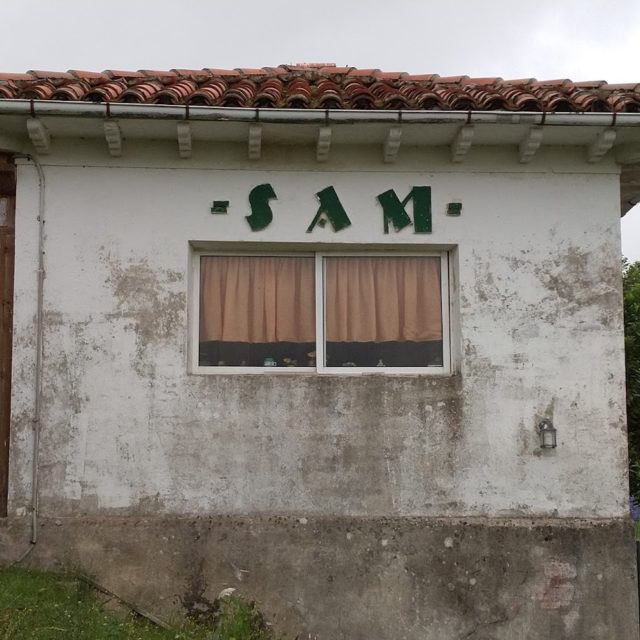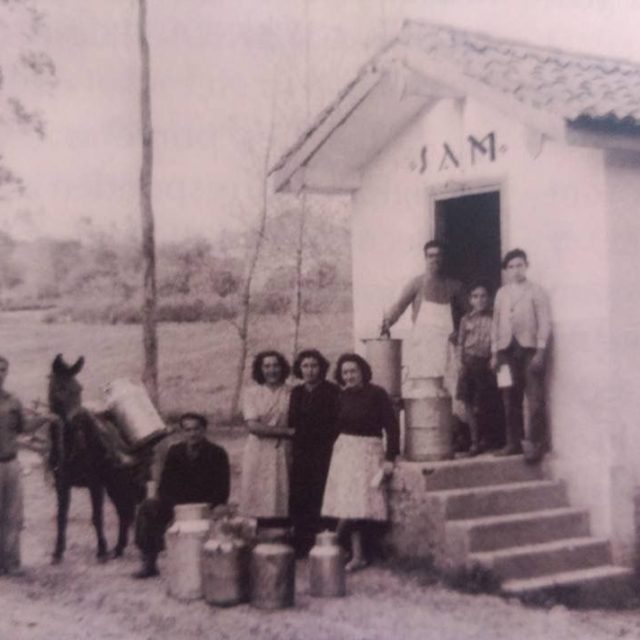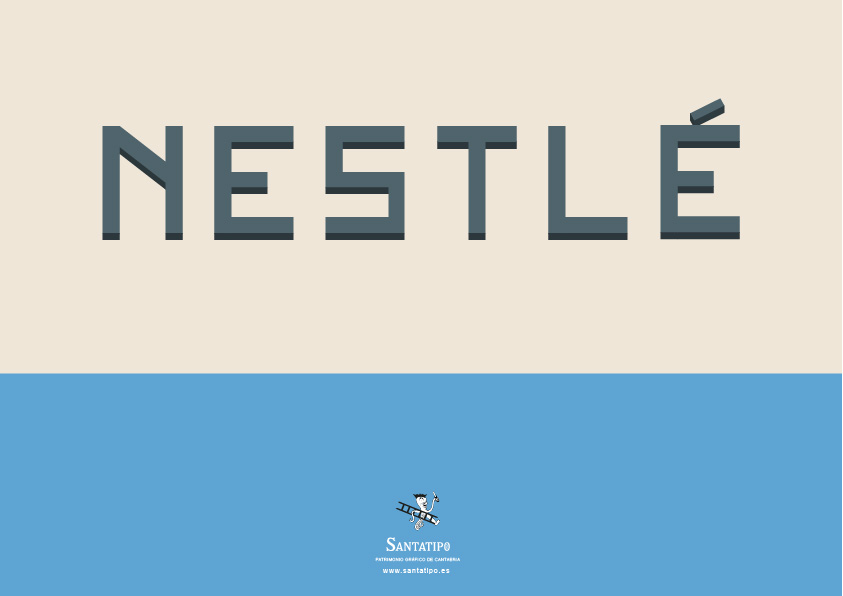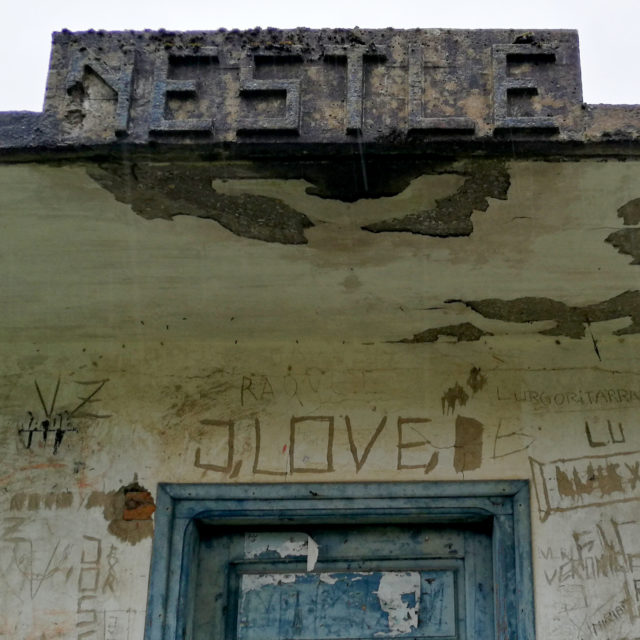
Puesto de Recogida de Leche de Nestlé (ca. 1930) Rasines
Detalle rótulo y tipografía geométrica que construye el logo, hecha en piedra / Foto: Santatipo
Reproducción
CONTEXTO
La leche ha sido una industria predominante en Cantabria, es por ello que es habitual ver aún por algunos pueblos y carreteras, los característicos puestos de leche de la Cooperativa SAM (Sindicatos Agrícolas Montañeses) que abrieron su fabrica en Renedo de Piélagos en 1931 y que estuvo como tal hasta el año 1977 cuando pasó a ser parte del grupo de empresas lactáreas.
Estas puestos tienen su lógica, dado que es la leche la materia prima y todo se basaba en una cadena estudiada de suministros. Estos puestos estaban preparados para que los ganaderos depositasen la leche y camiones de la fábrica pasaban a recogerla. Eso a nivel industrial. A nivel social, era algo más el ir a depositar la leche porque servían como punto de encuentro colectivo.
Puesto adaptado como vivienda en Quijano de Piélagos / Foto: Santatipo
Pero ¿sabes quien fue el que introdujo este sistema? Fue NESTLÉ que se instaló en la Penilla de Cayón en 1905, quien implementó esta estrategia.
Por tanto fue habitual durante un tiempo ver los puestos de unos y de otros, y tenía como característica el color:
• Azul eran los de la NESTLÉ
• Verdes los de la SAM
Pero como grandes rivales en la industria, junto a otras pequeñas fábricas, a comienzos de los años 30 hubo un enfrentamiento judicial por temas de costes y otro asuntos económicos. Finalmente en abril de 1933, se dictó sentencia que supuso un revés para la Nestlé y le obligo a que el 18 de mayo de ese año se anunciase el cierre de la gran mayoría de los puntos de recogida.
Por tanto, desde ese momento, fue la SAM la gran beneficiada y es, a pesar de muchos han desaparecido o están abandonados, que sigamos viendo esos míticos puestos verdes con su icónica tipografía.
Y sea muy raro ver ya uno de Nestlé. Por eso el poder importante e desde un punto de vista patrimonial por todo lo que nos dice. A nivel arquitectónico, económico y social.
Los puestos de leche deben ser preservados y protegidos, por lo que en ellos implica social y culturalmente en nuestra región.
Puesto de recogida en los años 50. Fuente: desconocida.